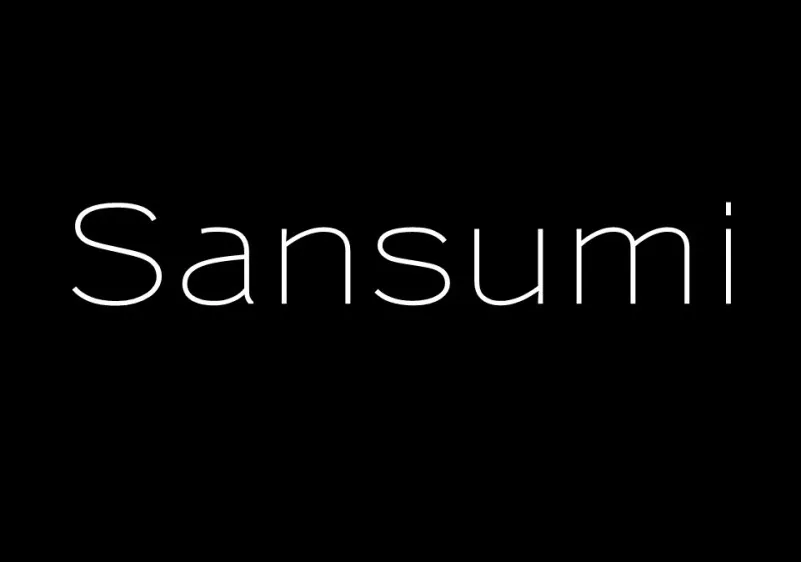
Sansumi Sans Serif Font
A Sansumi Sans Serif Font foi criada com a intenção de manter uma regularidade e um tipo geométrico de sans serif que tendem a ser facilmente recebidos pelo leitor, oferecendo grande possibilidade de uso. Com sua personalidade simples, robusta e forte, ela pode facilmente se misturar com um amplo conjunto de projetos. Adicione-a aos seus ideias criativas e veja como ela os destaca! Esta fonte tem uma aparência minimalista que se ajusta perfeitamente a múltiplas aplicações, tornando-se uma escolha ideal para designers em busca de uma solução versátil. Seu design limpo e elegante complementa qualquer tipo de projeto, seja ele digital ou impresso. Composta por linhas firmes e texturas sutis, a Sansumi Sans Serif é perfeita para quem busca tanto modernidade quanto simplicidade no seu trabalho.